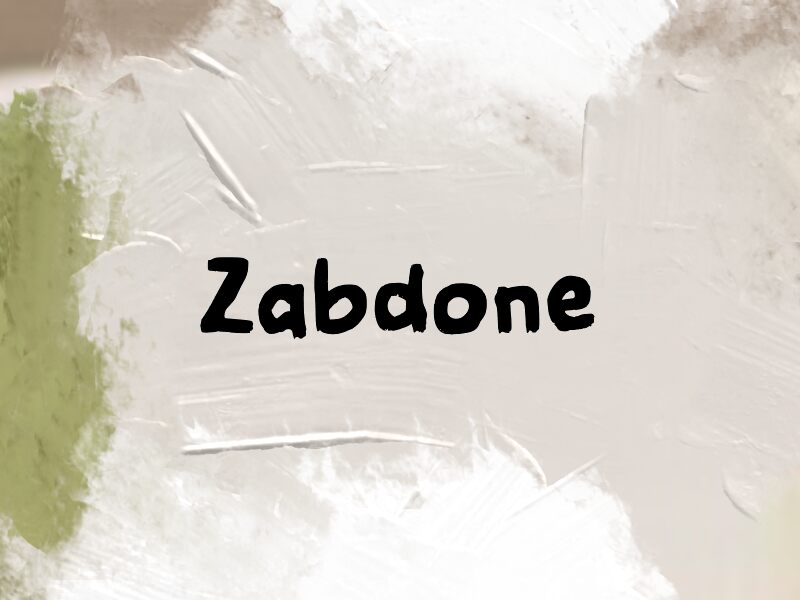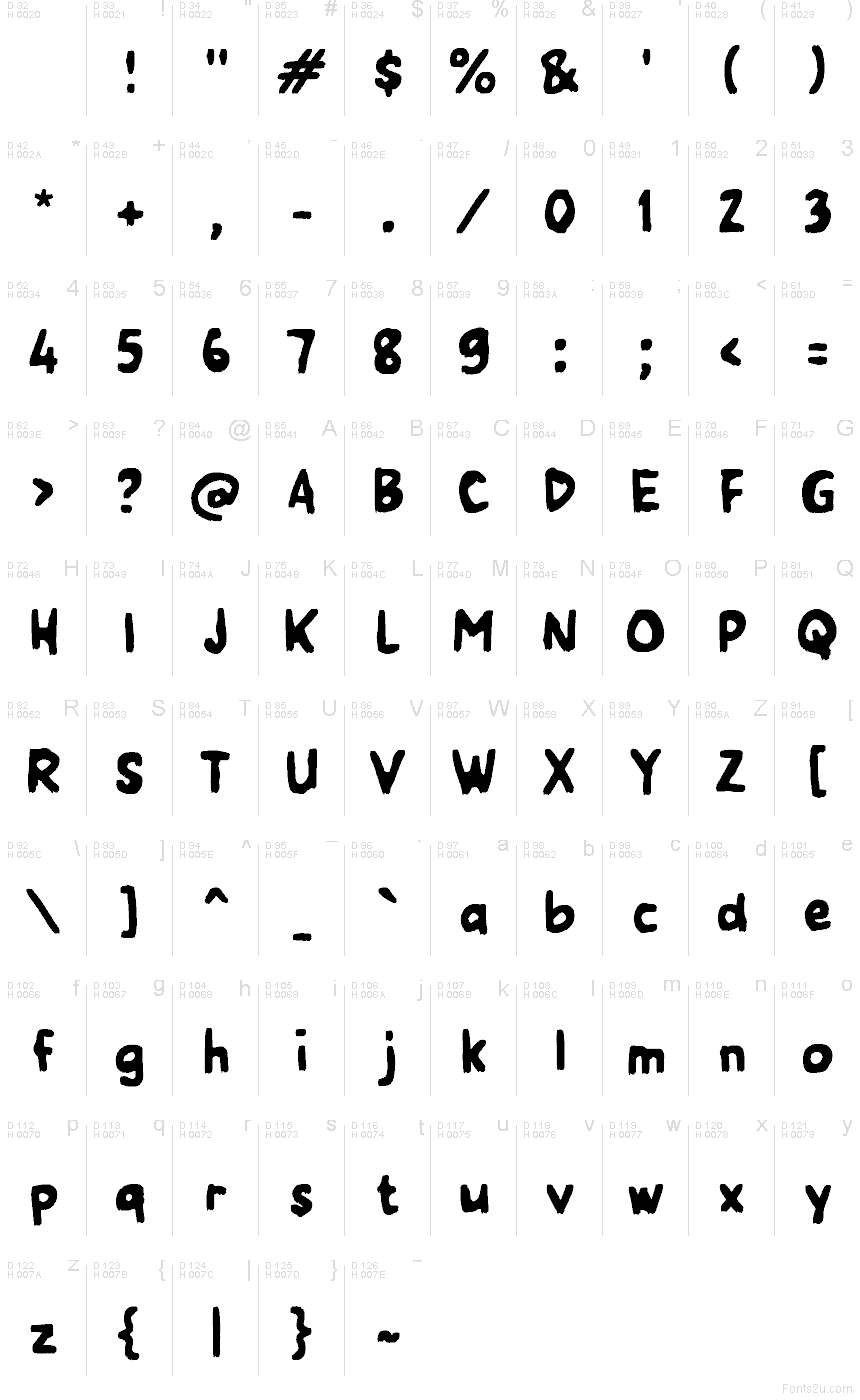
Zabdone, bezplatné brush písmo od Wep, má v sobě úderný rytmus ručně malovaných nápisů. Zaoblené tvary a useknuté konce tahů dodávají písmu hustotu a autenticky řemeslný vzhled. Díky lehce nepravidelným okrajům a kompaktním siluetám působí design jako čerstvě nanesený inkoust, což je příjemná změna oproti příliš hladkým digitálním štětcům.
Tato textura vynikne na plakátech, v brandingu food trucků, na obalech alb, na obalech produktů nebo v grafice pro sociální sítě, kde písmo musí působit bezprostředně a hmatatelně. Krátké nadpisy těží především z výrazného pohybu štětce, který vytváří drsný, malířský dojem, aniž by sklouzl ke graffiti nebo k nevkusným dekorativním fontům.
Zabdone